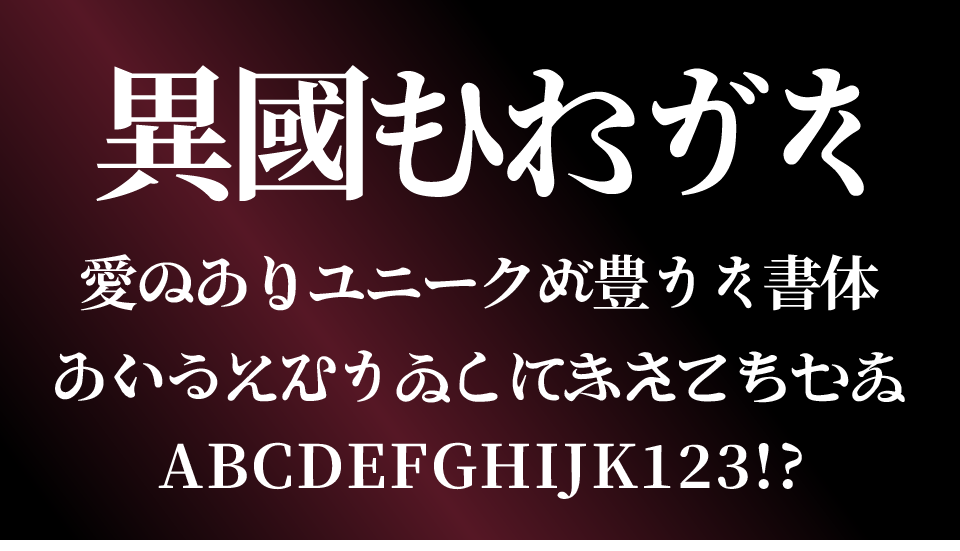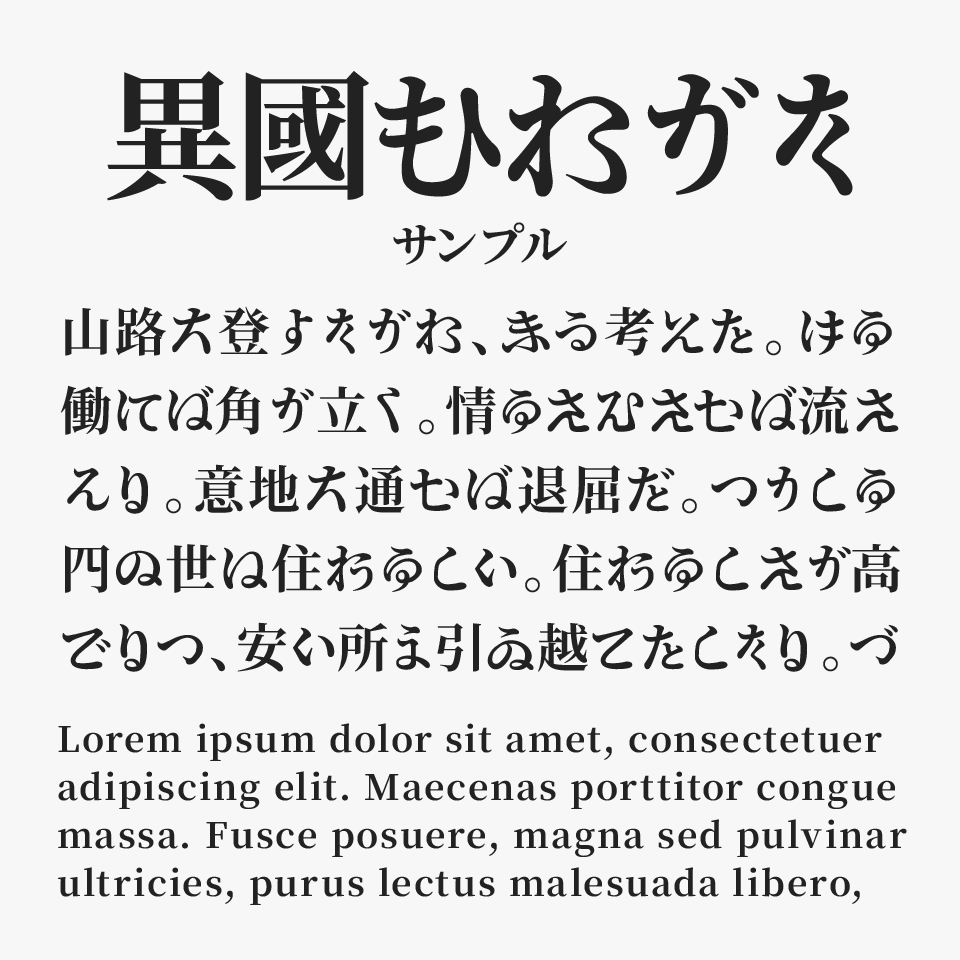
異國ひらがな
異國ひらがなフォントは、明朝体の骨格をベースに、ひらがなに独特の崩しを取り入れて異国情緒を表現した個性的な明朝体フォントです。
どこか古い写本や異国の文字を思わせる崩れ方をしており、読み慣れた日本語のようにも感じるけど、一瞬だけ異世界に迷い込んだような感覚を感じる面白いフォントです。
漫画やゲームの吹き出しや、歴史小説の装丁や和風ファンタジーのタイトルにも相性が良さそうです。